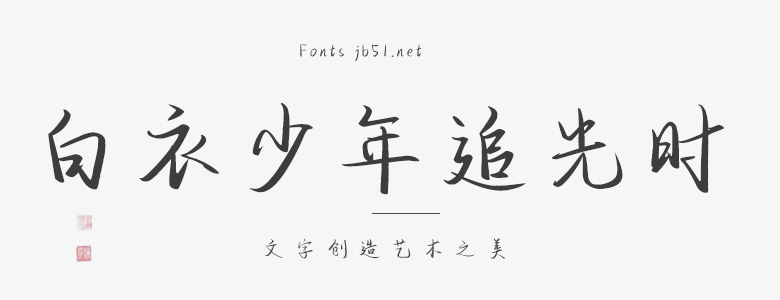
白衣少年追光時(shí)是一款獨(dú)特且富有詩意的字體,設(shè)計(jì)靈感源于青春的熱情與追求。這款字體的線條流暢,字形優(yōu)雅,給人一種白衣少年在陽光下奔跑的感覺,充滿了活力和朝氣。 字體細(xì)節(jié)豐富,獨(dú)具匠心。每個(gè)字母的起筆、收筆以及連接處都經(jīng)過精細(xì)的設(shè)計(jì),使得每個(gè)字母看起來仿佛是正在奔跑的少年,朝氣蓬勃。同時(shí),字體的曲線部分流暢自然,給人一種舒適、柔和的感覺,如同少年們在陽光下歡笑、玩耍的場景。 白衣少年追光時(shí)的字體風(fēng)格獨(dú)具特色,不僅展現(xiàn)了青春的活力與激情,還蘊(yùn)含著對美好未來的向往與期待。這種獨(dú)特的視覺體驗(yàn)讓人在使用這款字體時(shí),能夠感受到一股積極向上的力量,如同白衣少年們不斷追求夢想的勇氣與決心。 總的來說,白衣少年追光時(shí)是一款富有創(chuàng)意和青春氣息的字體,適合用于各種年輕、陽光、積極向上的品牌或場合,能夠很好地傳遞出青春活力和積極向上的信息。